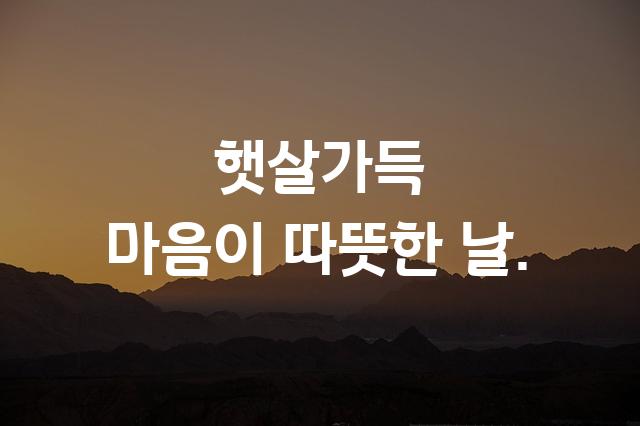
한수원 한울림체는 꽉 찬 고딕 스타일과 장식적 요소가 조화롭게 어우러진 폰트입니다. 굴린 고딕 특성이 돋보이며, 강렬하면서도 섬세한 인상을 줍니다.
한수원 한울림체은(는)
기본 고딕, 굵은 고딕, 장식 스타일, 단단함, 별모양/패턴 계열의 생김새를 가지고 있으며
웹/앱 디자인, 프레젠테이션, 보고서/문서 등에서 자주 활용되며, 효과적인 메시지 전달에 적합합니다.
이 폰트는 공공/정부, 금융/비즈니스, 환경/에너지 분야에 잘 어울리며,
신뢰감, 명확한, 전문적인 느낌을 담고 있는 것이 특징입니다.
이 폰트와 유사한 폰트로는 Noto Sans, Roboto, Gotham 등이 있어요. 함께 비교해 보시면 좋습니다!